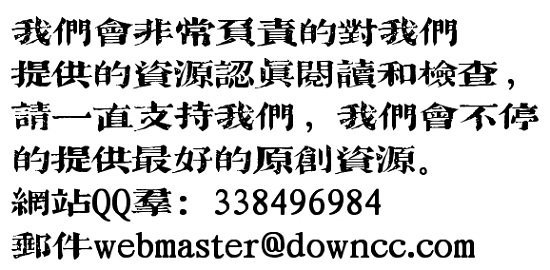
吉頁(yè)古老宋字體
吉頁(yè)古老宋ttf字體是孫新恒新推出的一款古宋體,字跡上很有印刷字體庚哥,支持繁簡(jiǎn)體輸入,更顯質(zhì)樸復(fù)古,讓你的文字都帶著一股古色生香的韻味,喜歡的朋友就來(lái)綠色資源網(wǎng)試試吧!
孫新恒吉頁(yè)古老宋體特色
吉頁(yè)古老宋延續(xù)了宋體書(shū)法字體飄逸清揚(yáng),采用了印刷字體的墨跡清香,讓文字更有古風(fēng)特色,行筆間流暢舒緩,給人極佳的視覺(jué)呈現(xiàn)和獨(dú)特的魅力呈現(xiàn)!可以廣泛運(yùn)用在藝術(shù)設(shè)計(jì)、平面設(shè)計(jì)、廣告設(shè)計(jì)、包裝設(shè)計(jì)等領(lǐng)域!